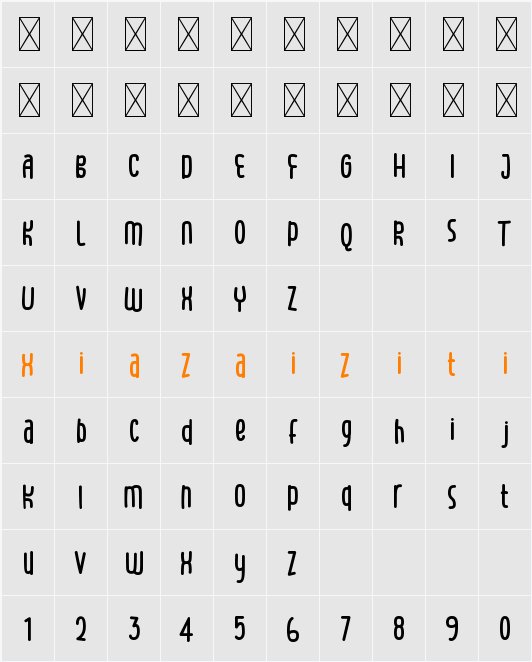
World Madly
World Madly,这款字体结构工整、笔画清晰,兼顾美观与易读性,适用于标题、正文、海报、包装、LOGO 等多种场景。字形优雅稳定,风格百搭耐看,适配日常排版与创意设计,让文字呈现更舒适、更具质感。World Madly一笔一画,皆是细节,以均衡的比例、流畅的线条打造舒适视觉体验,字形端正大气,风格简约现代。无论是商业设计、品牌宣传还是日常排版,都能轻松驾驭,让文字更有格调与力量。World Madly字体下载。
• 制造商: Putracetol Studio, Karanganyar.
• 设计师: Putra Novembria Candra Kusuma